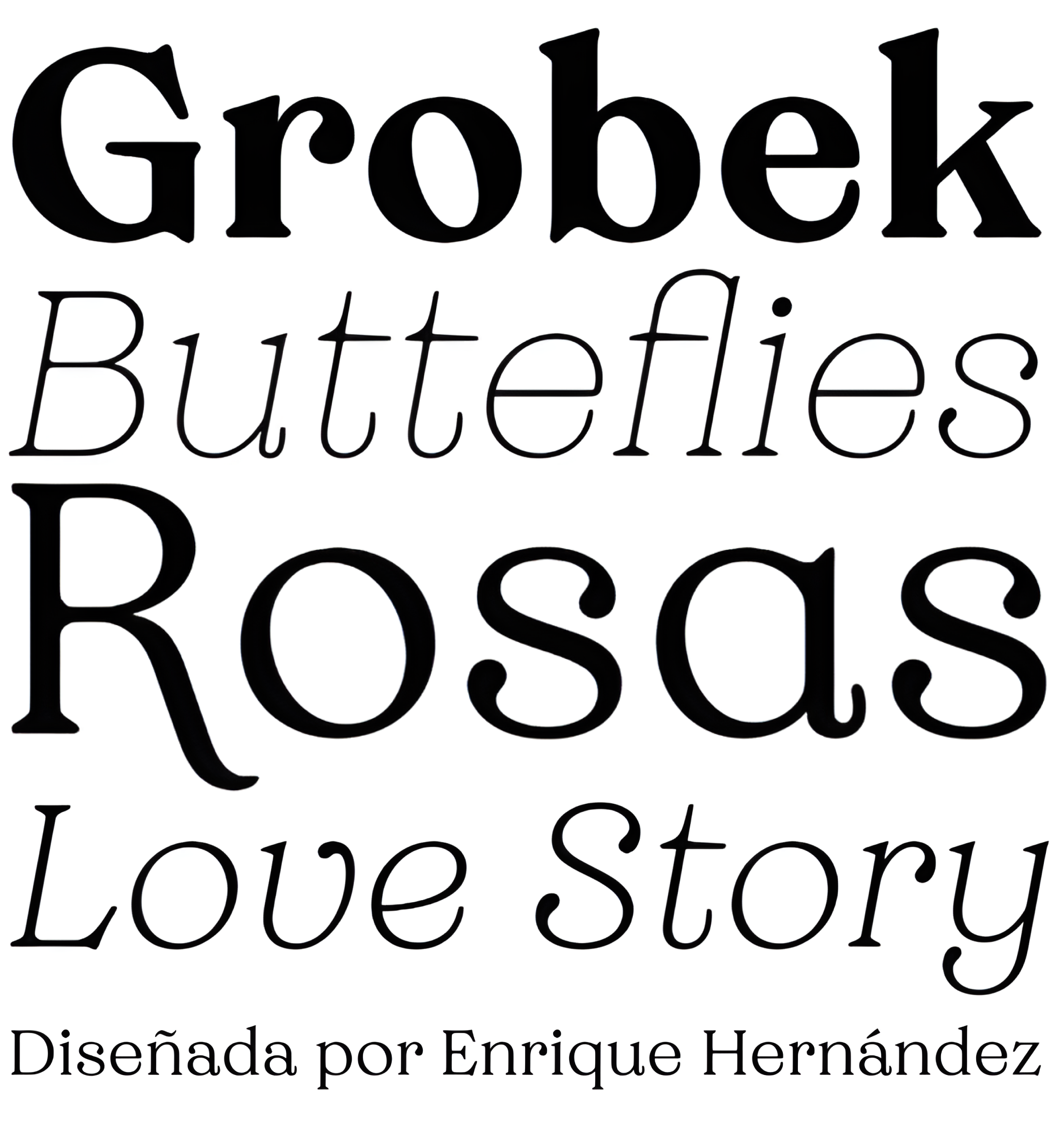
| Año | 2020 |
| Créditos | Enrique Hernández |
| Descripción | Grobek es un tipo de letra con gracias inspirado en las fuentes Garamond y American Typewriter, así como en los tipos de letra clásicos del siglo XV. Sus principales características son un acento diagonal y suaves terminales curvados en forma de lágrima. |
| Familia(s) | Thin, Thin Italic, Light, Light Italic, Normal, Normal Italic, Regular, Regular Italic, Medium, Medium Italic, Bold, Bold Italic, Black, Black Italic, Heavy, Heavy Italic, Alt Thin, Alt Thin Italic, Alt Light, Alt Light Italic, Alt Normal, Alt Normal Italic, Alt Regular, Alt Regular Italic, Alt Medium, Alt Medium Italic, Alt Bold, Alt Bold Italic, Alt Black, Black Italic, Alt Heavy, Alt Heavy Ital |
| Estilos | 32 |